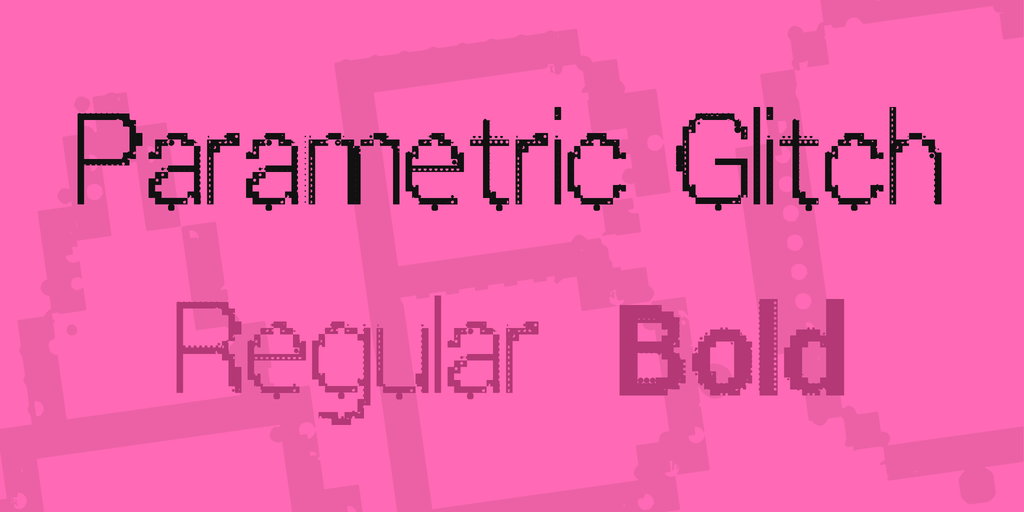
Parametric Glitch Font Family – Download Grátis
A fonte ‘Parametric Glitch’ é uma criação única no meio das fuentes pixel art, desenvolvida pelo designer Hamilton. Esta fonte traz a essência do estilo glitch, misturando elementos de tecnologia futurista com um toque de desorganização criativo. Suas linhas finas e distorcidas formam letras com uma personalidade peculiar e vibrante que se adequa perfeitamente para design gráfico que deseja transmitir uma mensagem de novidade ou inovação sem deixar de lado a diversão e o encanto do glitch art. A ‘Parametric Glitch’ não é apenas uma fonte, ela é uma experiência sensorial. Permite aos designers criar textos em um formato único que se adapta à linguagem e ao contexto de cada projeto. Seja para uso em interfaces digitais ou design gráfico digital, essa fonte pixel art vai deixar seu projeto destaca-se entre a multidão. Seja você criando uma identidade visual futurista ou simplesmente querendo dar um toque especial a suas criações, ‘Parametric Glitch’ é uma escolha inteligente para qualquer projeto que busque algo mais do que uma fonte pixel art tradicional.